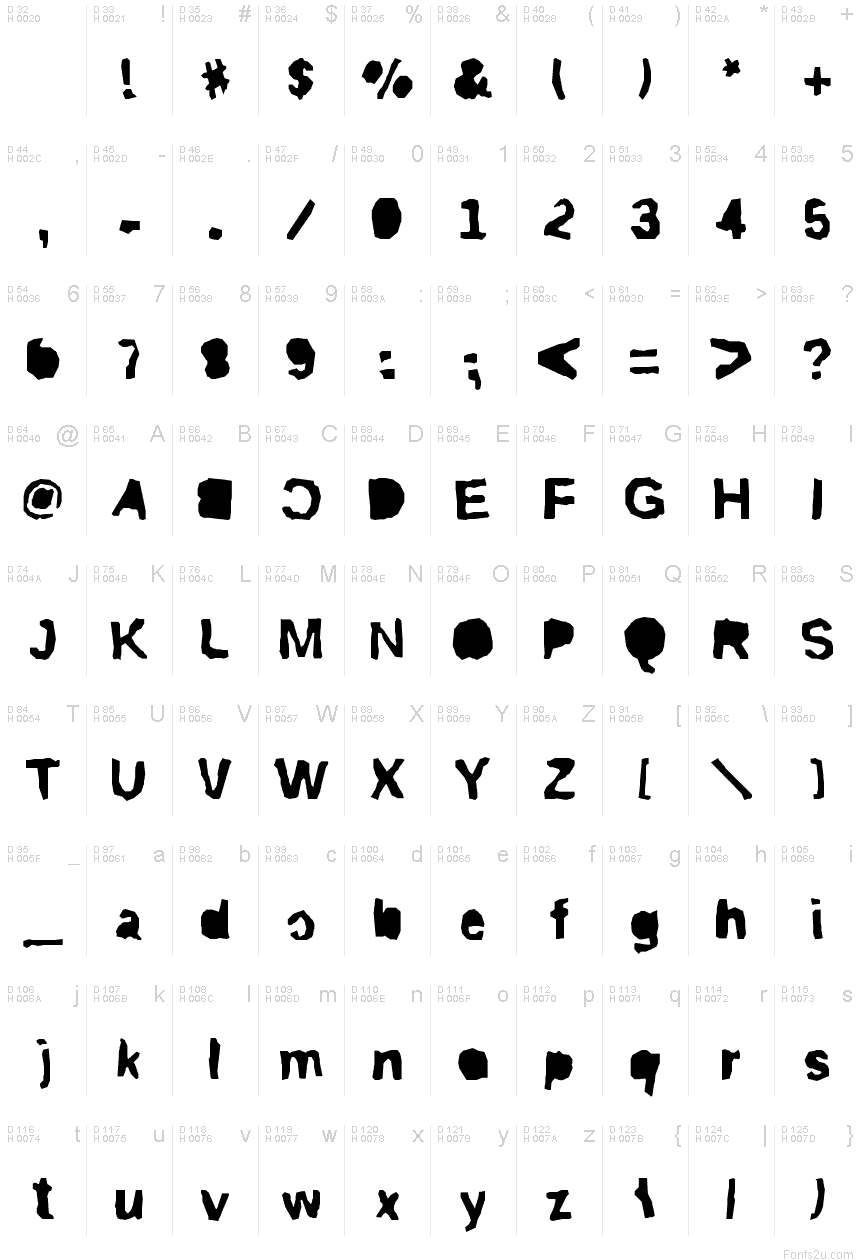
rip TRASH Cut Mirror von Manuel Viergutz ist eine kostenlose, verzerrte Displayschrift aus stumpfen und zerrissen wirkenden Buchstabenformen. Ihre schweren Silhouetten brechen in zackige Kanten und abrupte Kerben auf, wie aus grob geschnittenem Papier zusammengesetzt.
Die Konstruktion aus gerissenem Papier lässt sich auf Musikplakaten und Albumcovern mit Collage-Bildern verbinden, wo die Schrift zu einem Teil der handgemachten Textur wird. Sie eignet sich auch für Streetwear-Merchandise, Skate-Grafiken und raues Event-Branding.
rip TRASH ist eine Headline-/Display-/rohe handgemachte Schrift mit sechs Stilen und 100 Glyphen, einschließlich akzentuierter Zeichen.
- regular
- mirror
- cut
- cutMIRROR
- round
- roundMIRROR